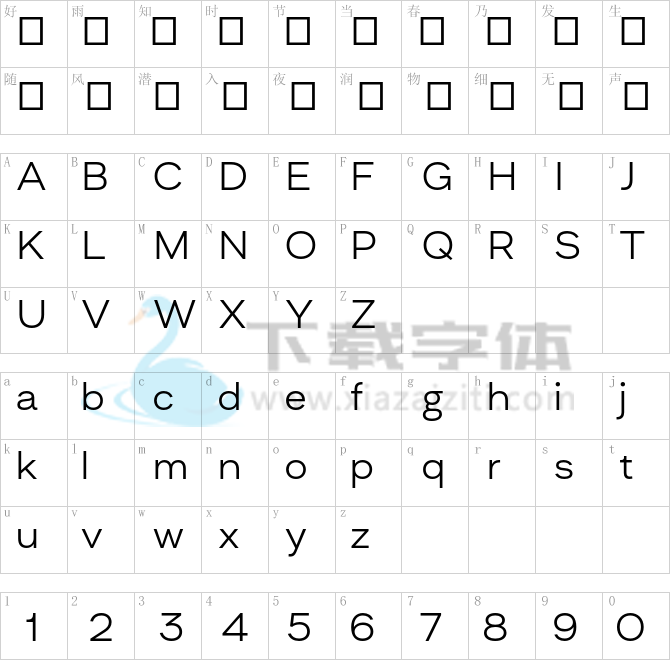
Asket Extended.otf字体下载,这款字体结构工整、笔画清晰,兼顾美观与易读性,适用于标题、正文、海报、包装、LOGO 等多种场景。字形优雅稳定,风格百搭耐看,适配日常排版与创意设计,让文字呈现更舒适、更具质感。Asket Extended.otf字体下载一笔一画,皆是细节,以均衡的比例、流畅的线条打造舒适视觉体验,字形端正大气,风格简约现代。无论是商业设计、品牌宣传还是日常排版,都能轻松驾驭,让文字更有格调与力量。Asket Extended.otf字体下载字体下载。